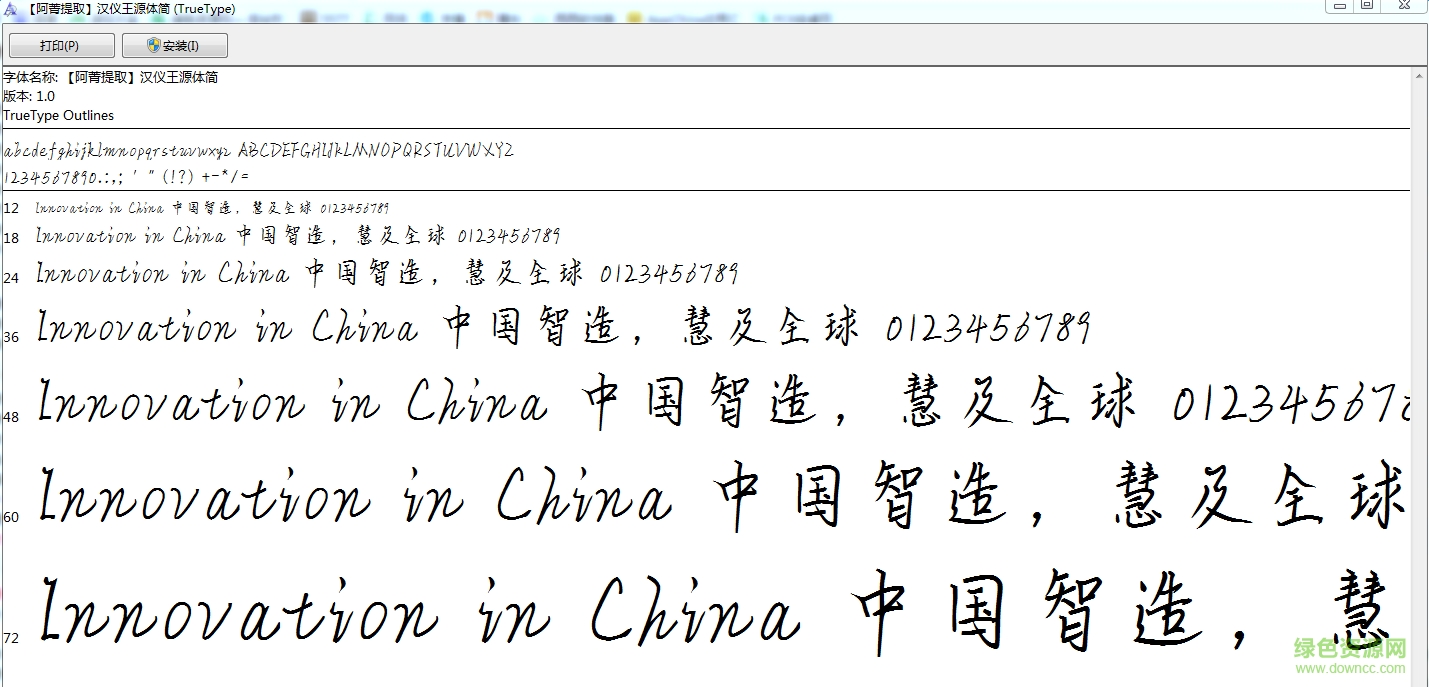
漢儀王源體
漢儀王源字體是一款漢儀類王源字體軟件,王源的字體給人非常舒服的感覺,深受廣大年輕人的喜愛,還有更多好看字體盡情期待,歡迎到綠色資源網(wǎng)下載體驗!
王源的字曝光后,清秀、小巧的字體得到好評。就在近日,其字體被漢儀字庫收錄。在王源以往詮釋的角色中,少男氣十足,小編此次給大家?guī)淼氖菨h儀王源字體。